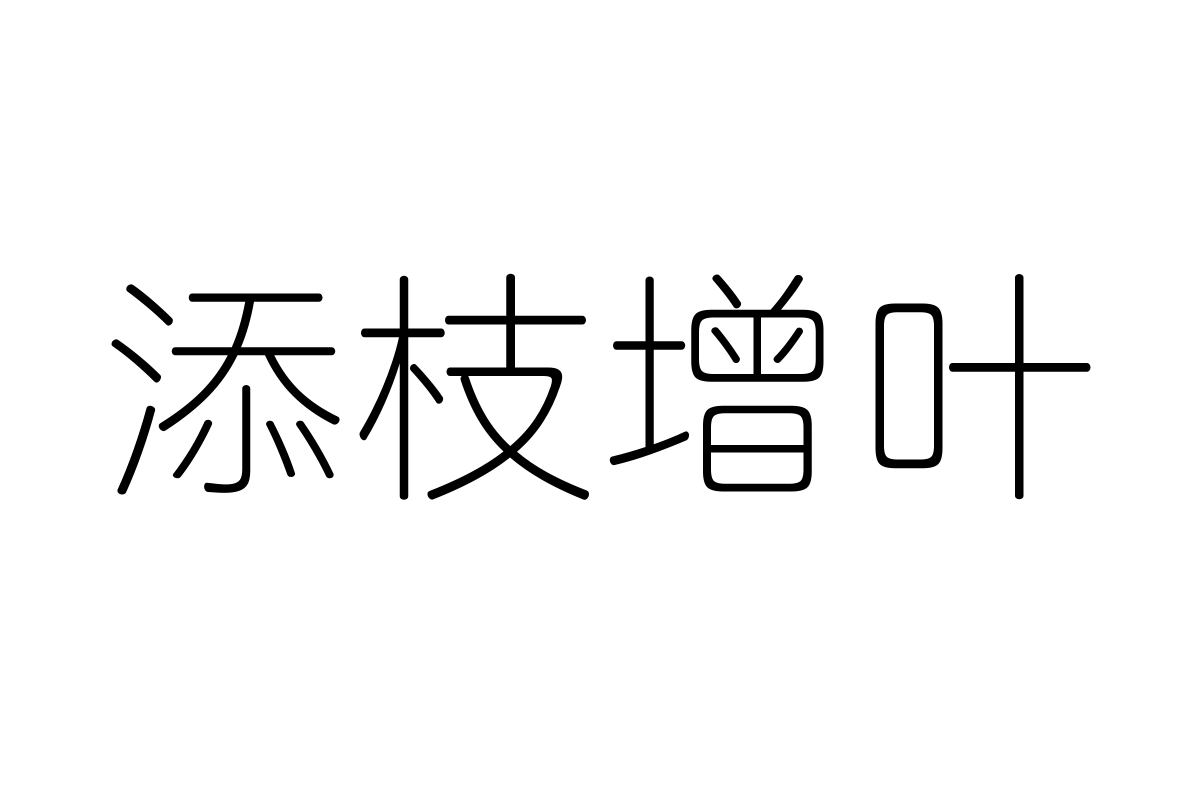
汉仪正圆-35字体是汉仪字库近期发布的一款新的排版字体。该字体包含35S~95S共计七个字重,提供TrueType、PostScript两种轮廓格式。
汉仪正圆-35字体家族目前有七个字重,分别是35S、36P、37P、38P、39P、40P和42P。其中35S至42P分别对应了常用的纤细体(ExtraLight)、细体(Light)、常规(Regular)、准黑(Medium)、中黑(Semibold)、粗体(Bold)以及大黑(Heavy)。这种多样化的字重选择使得用户可以根据自己的需求和应用场景选择合适的字体样式。
此外,汉仪正圆-35字体采用GB18030-2000大字符集,收录简体字、繁体字、生僻字和异体字等共计27533个字符。字体采用OpenType格式封装,有两个版本,一个采用TrueType轮廓,另一个采用PostScript轮廓,质量都非常高。
总的来说,汉仪正圆-35字体是一款功能强大、适用范围广泛的字体,无论是在印刷媒体还是数字媒体领域都能发挥出色的表现。